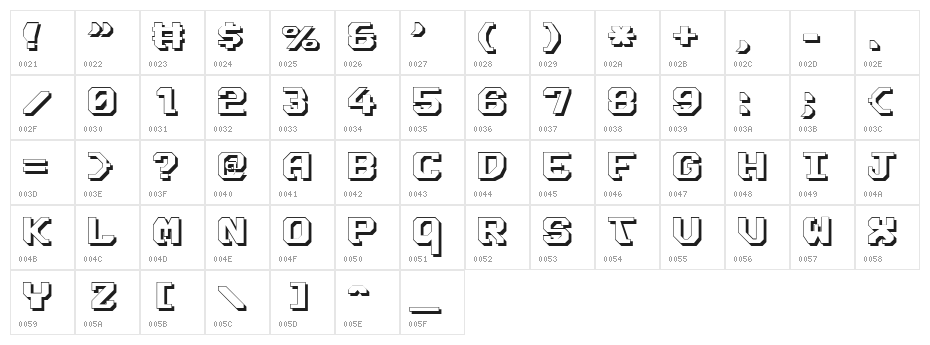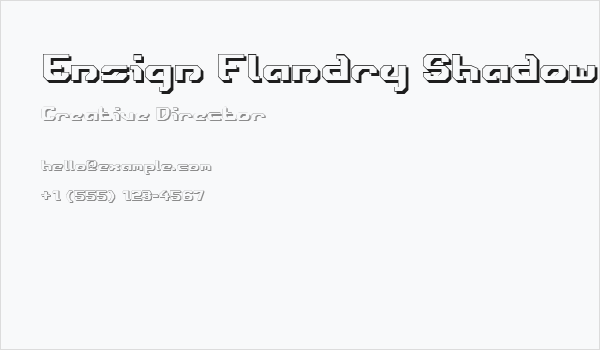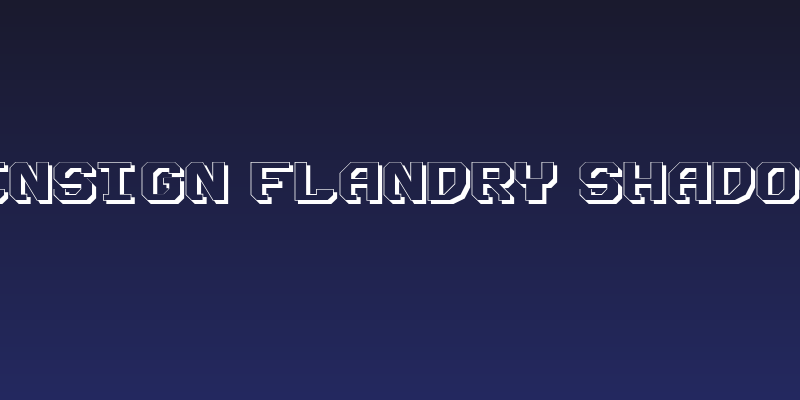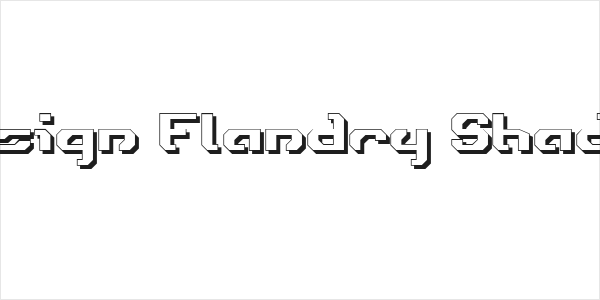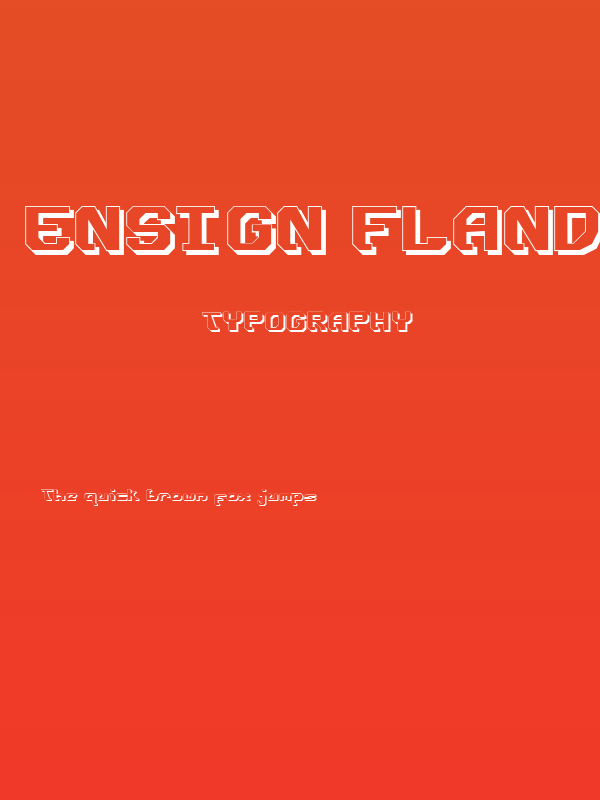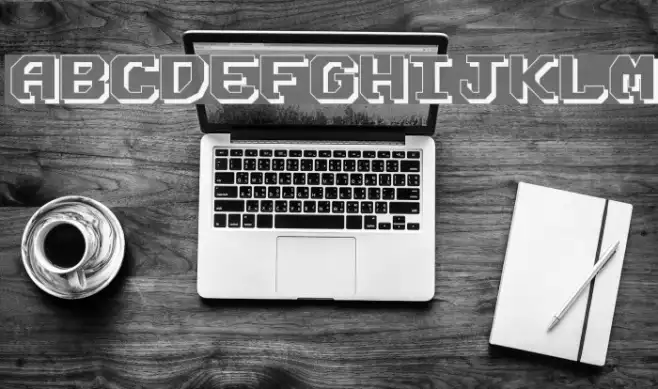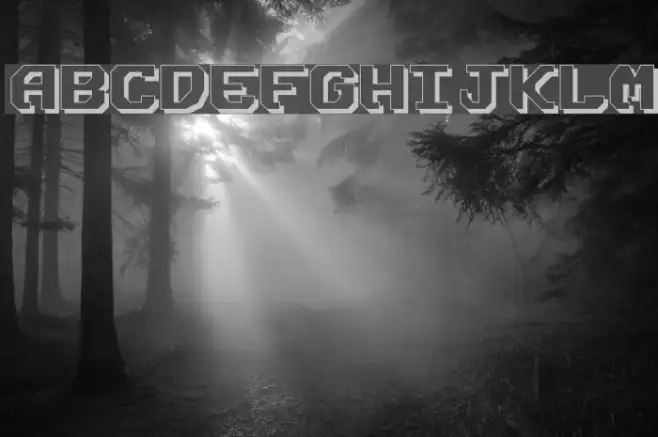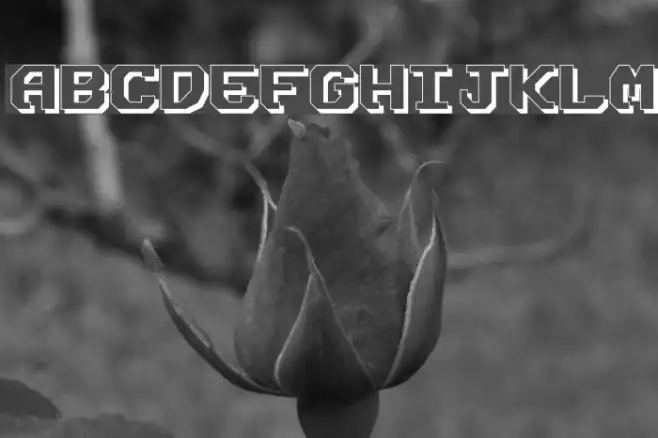
Ensign Flandry Shadow Font
| Vorgeschlagene Projekte | Ideal for posters, logos, video game graphics, and any design needing a bold, eye-catching typeface. |